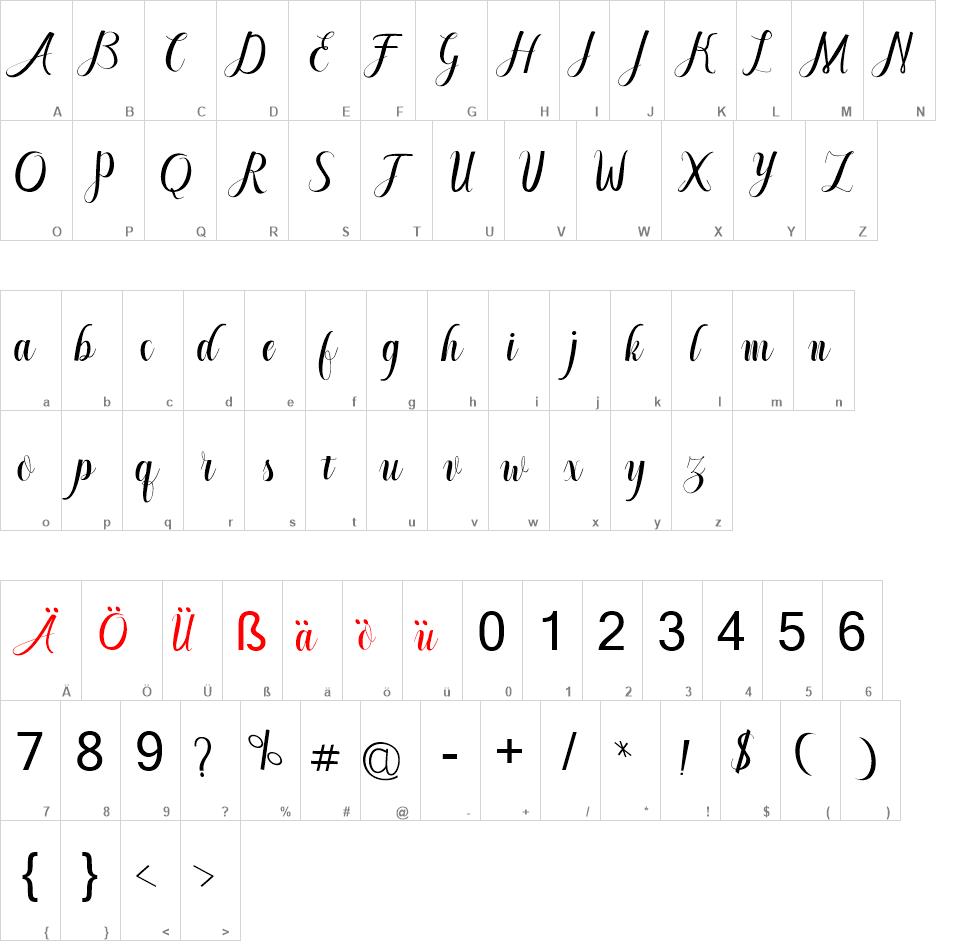
Cintella
Cintella font
Cintella
Cintella Script ist eine Skriptschriftart, die die charakteristische Handschrift hat, sie ist sehr geeignet, um bestimmte Etiketten- und Event-Geschäfte zu erstellen, und Sie könnten sie für ein einzigartiges Stück verwenden.